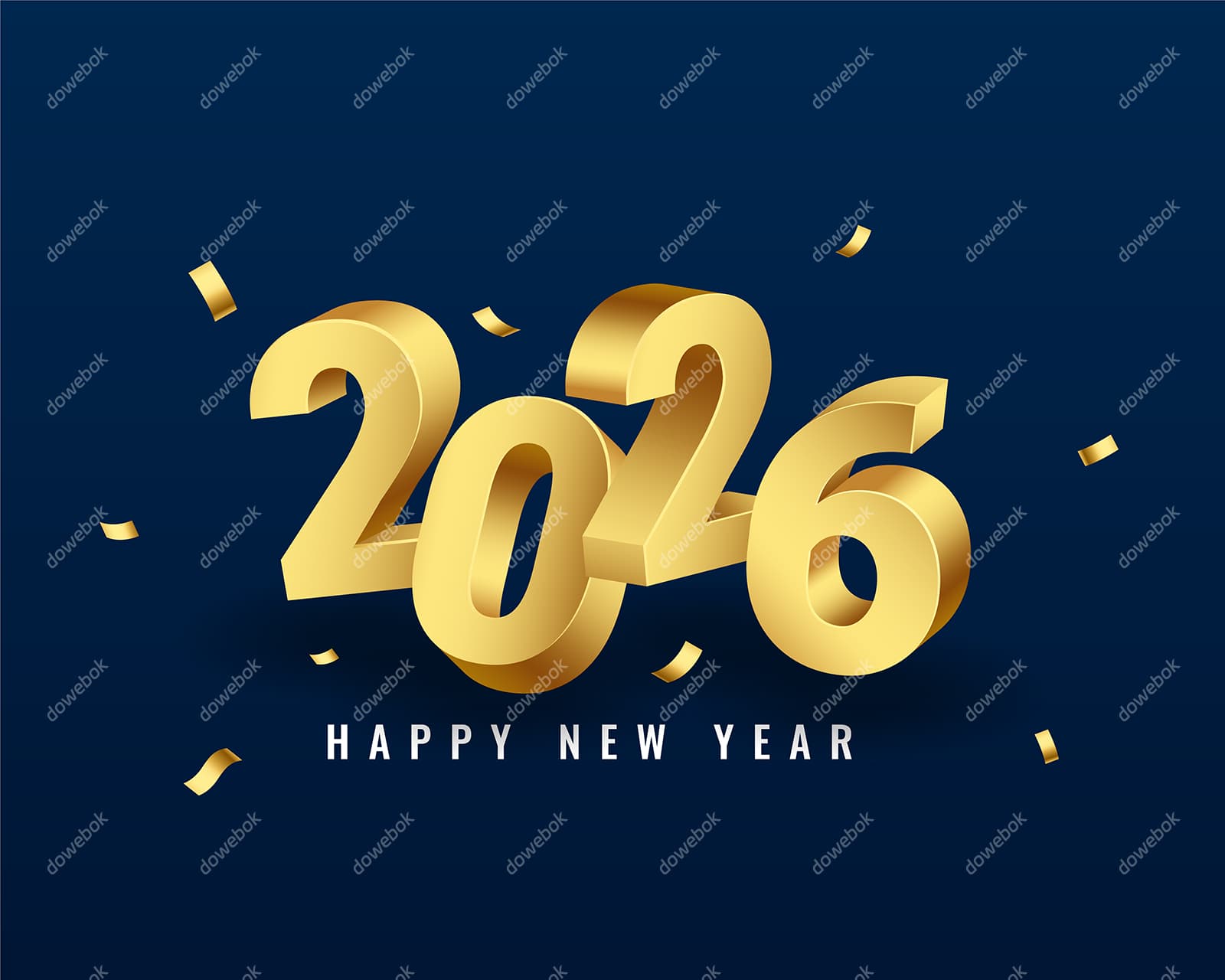
这是一款立体金色数字设计的 2026 新年快乐矢量素材,深幽的藏蓝背景上,立体金色的 “2026” 字体质感华贵,光泽感十足。数字周围散落着金色飘带装饰,下方配白色 “Happy New Year” 英文。整体黑金色调高级大气,立体字与飘带元素既显新年的热烈氛围,又以精致质感传递出奢华的仪式感,适配高端新年贺卡、活动海报等场景。